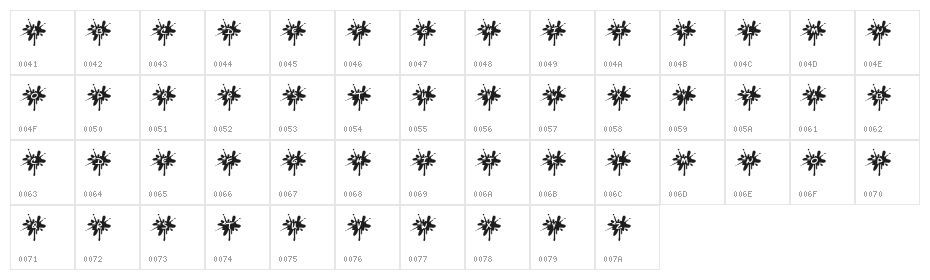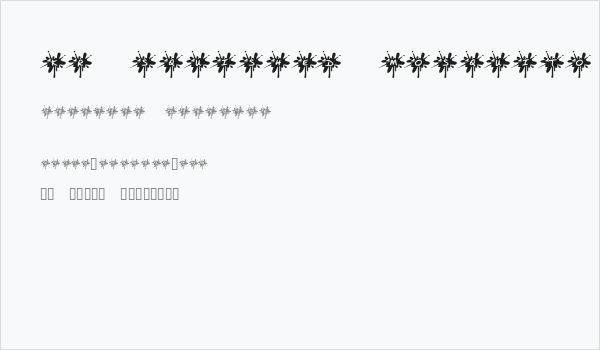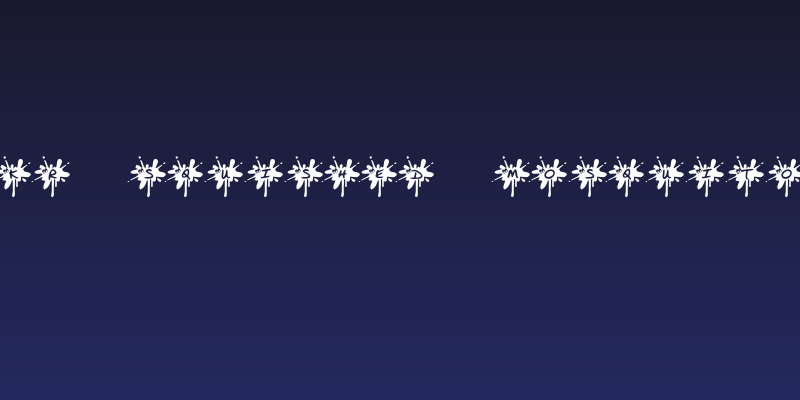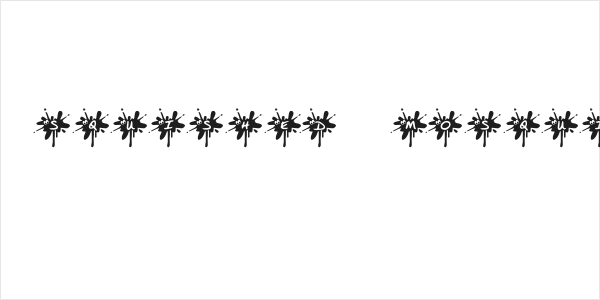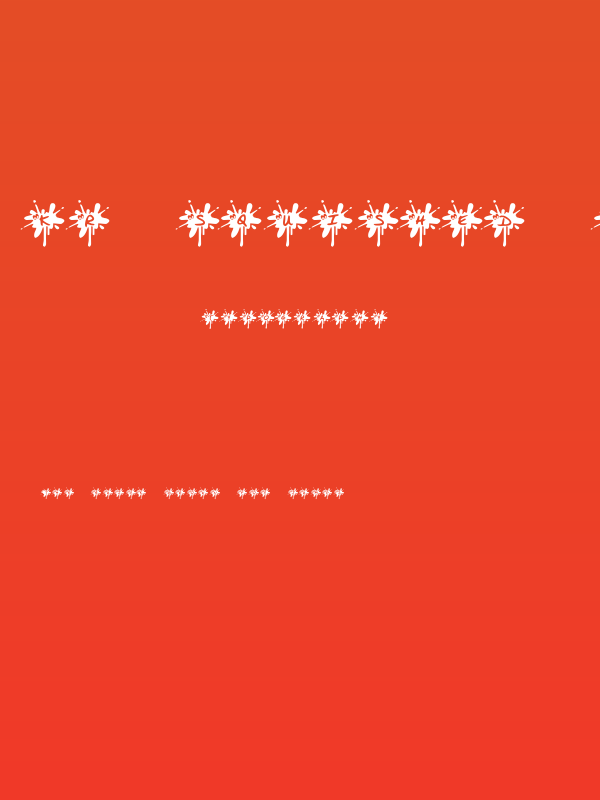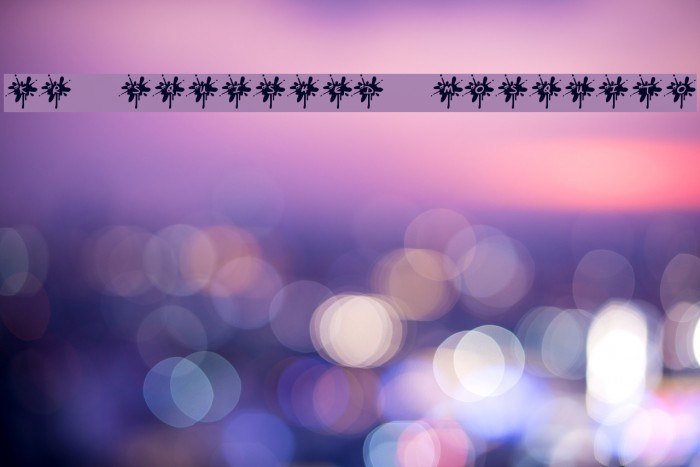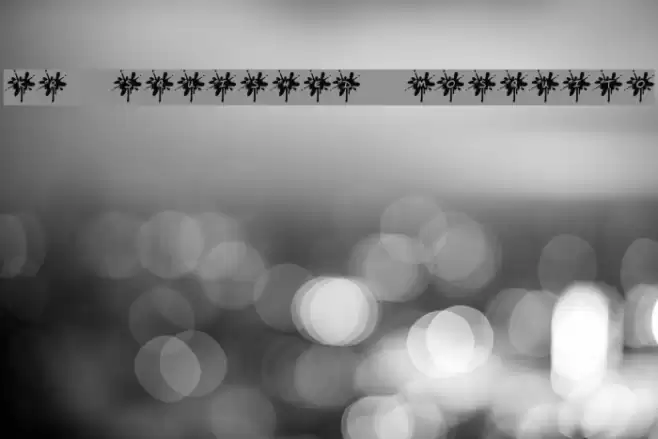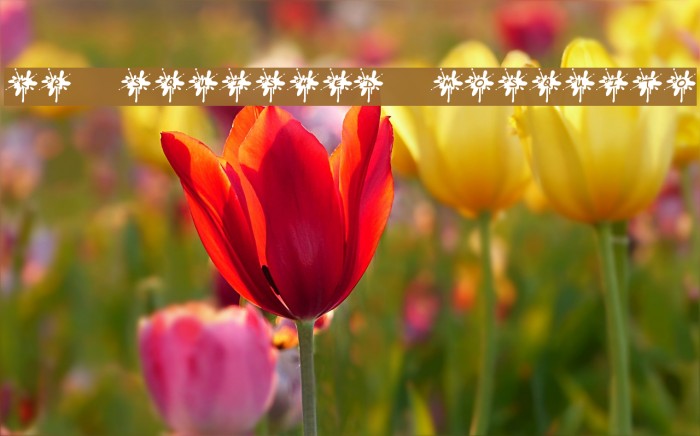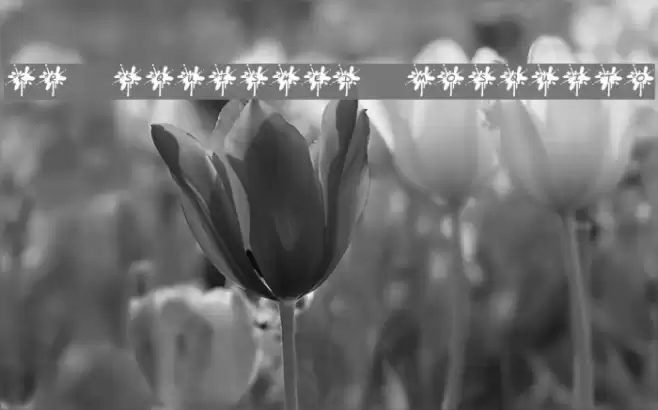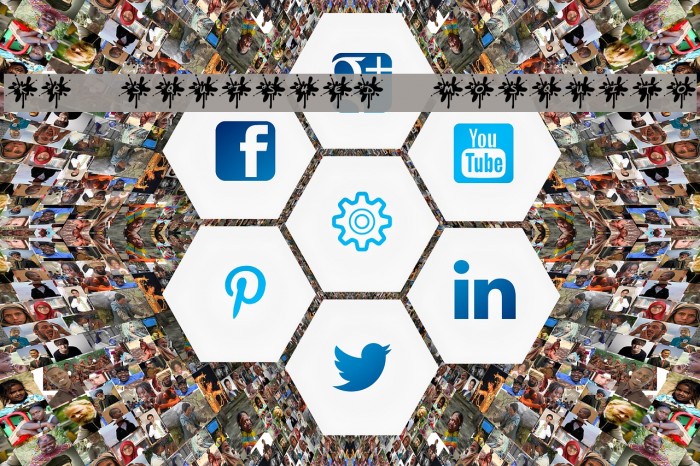
KR Squished Mosquito Font
| Anwendungsfall | Logos, Headlines, Posters |
| Vorgeschlagene Projekte | Ideal for children's book covers, playful posters, party invitations, or any project needing a fun and whimsical touch. |